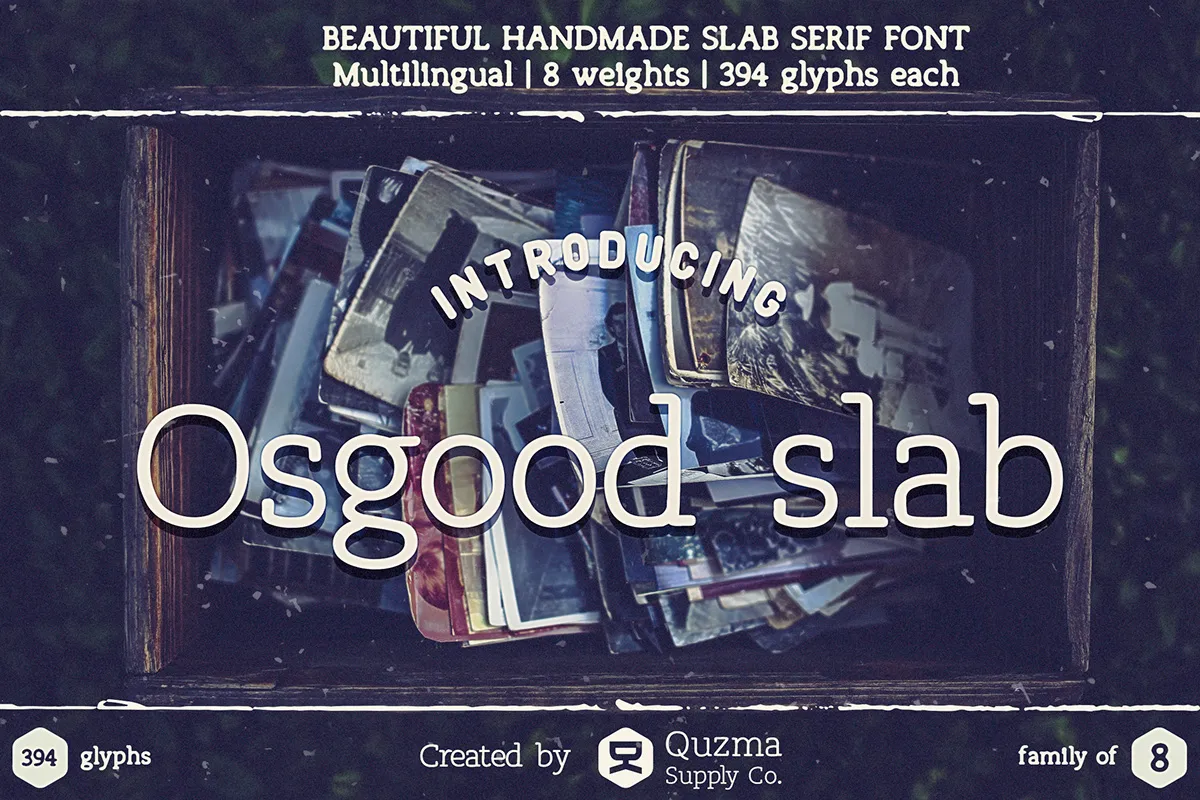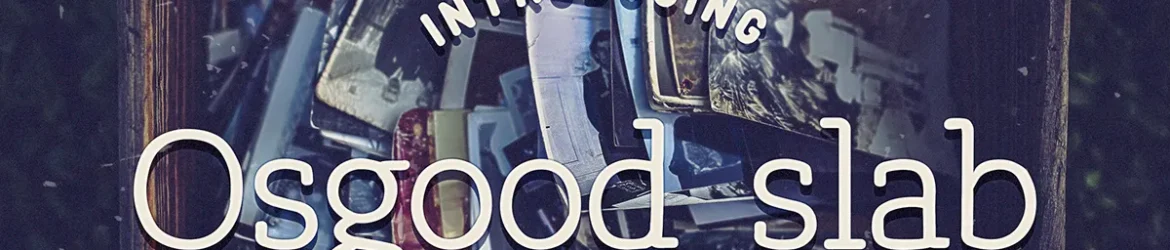
Osgood Slab é uma elegante fonte slab serif que traz a essência do estilo tradicional num formato moderno e versátil. Este tipo de letra foi criado pensando no usuário final, especialmente aquelas que buscam um equilíbrio perfeito entre aparência vintage e uso cotidiano. Perfeita para textos extensos ou parágrafos completos, é uma escolha ideal para ambientes onde a rusticidade da fonte desempenha um papel crucial, como em placas de sinalização ou artesanato vintage. Osgood Slab também se destaca no uso de citações e textos mais informais. Sua grande vantagem está na sua facilidade de leitura, tornando-a uma opção preferencial para qualquer aplicação que exija legibilidade em grandes proporções. Esta fonte representa um verdadeiro equilíbrio entre elegância clássica e funcionalidade moderna.